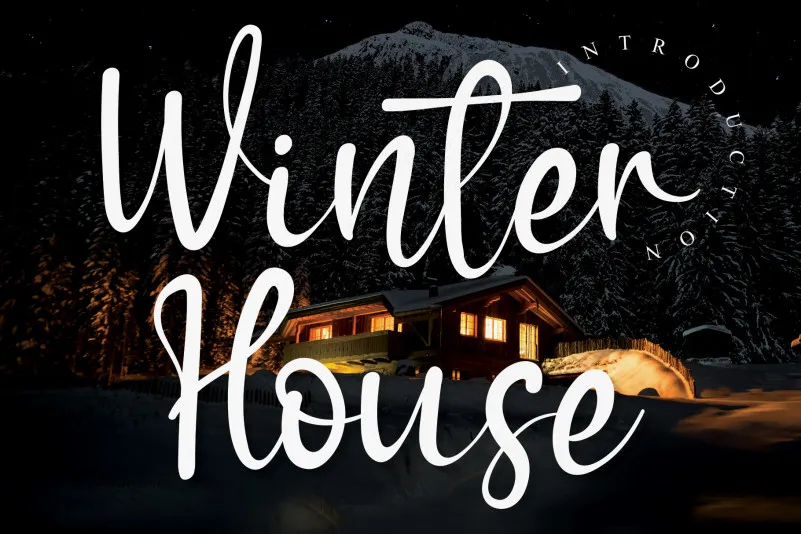
Winter House Script Font é uma tipografia feita à mão que oferece um toque elegante e confiável. Seu estilo sóbrio e carregado dá vida às suas ideias, transformando-as em realidade imediata. Esse fonte de escrita à mão também permite criar designs incríveis e surpreendentes. Ideal para acentuar o visual de qualquer projeto gráfico, desde cartões de aniversário até logotipos, Winter House Script é uma escolha perfeita tanto para designers quanto para aqueles que simplesmente desejam adicionar um toque autêntico a suas criações digitais. Além do seu uso como fonte principal, também pode ser usada em seções de contratos ou anúncios, proporcionando um ar único e personalizado à sua identidade visual. É perfeito para criar ambientes de escritório modernos ou estilos retrô que combinem o sofisticado com a simplicidade.